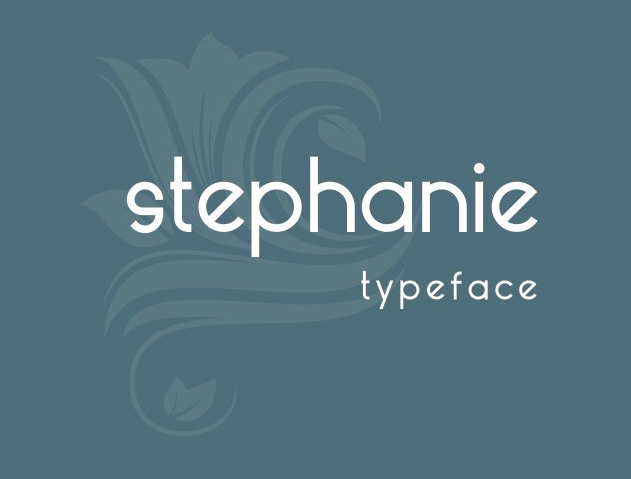
A Stephanie Font é uma elegante tipografia serifada criada pelo designer Hamilton. Inspirada nos sentimento femininos do amor e beleza, essa fonte sans-serif vem com uma sensação única e delicada que pode agradar tanto os profissionais de design quanto amantes da arte. Stephanie oferece um toque suave e sofisticado ideal para criar designs arredondados e harmoniosos, perfeito para criações personalizadas ou comerciais. Com seu formato atualmente limitado às letras minúsculas, a Stephanie tem o potencial de se tornar uma fonte indispensável. O designer Hamilton está trabalhando em um planejamento futuro que inclui incorporar letras maiúsculas, expandindo ainda mais as possibilidades criativas da Stephanie Font. Se você procura por um design elegante e sofisticado sem perder a delicadeza feminina, a Stephanie pode ser sua fonte perfeita para explorar. Com fácil acesso em formato otf ou ttf, é uma ótima opção para quem busca uma fonte de qualidade que se adequa a diversas necessidades gráficas.